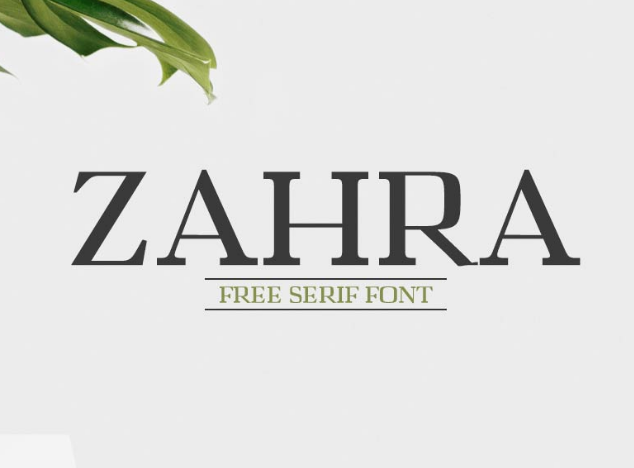
A Zahra Serif Font é uma elegante escolha para aqueles buscando uma tipografia serif que se destaca por sua ousadia geométrica e a adição leve de elementos de Arte Deco. Esta fonte é ideal para estilos modernos e limpos, especialmente adequada para logos, headlines e banners. Suas linhas sólidas permitem criar cada palavra com um toque elegante, tornando-a uma opção versátil que se adapta perfeitamente a diferentes projetos de design. A creativetacos trouxe Zahra Serif para compartilhar sua beleza única e seu poder de personalização, oferecendo aos designers uma fonte que pode estilizar qualquer texto em um ambiente visual moderno e sofisticado.